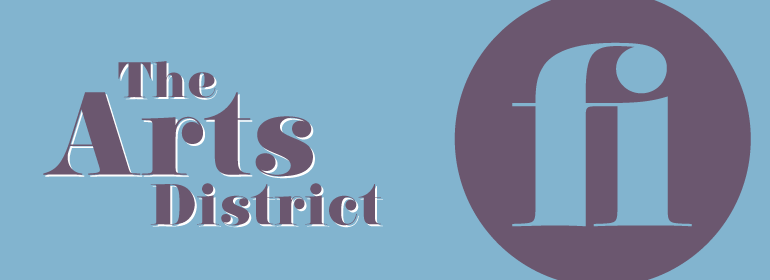
Carousel™
Carousel™,这款字体结构工整、笔画清晰,兼顾美观与易读性,适用于标题、正文、海报、包装、LOGO 等多种场景。字形优雅稳定,风格百搭耐看,适配日常排版与创意设计,让文字呈现更舒适、更具质感。Carousel™一笔一画,皆是细节,以均衡的比例、流畅的线条打造舒适视觉体验,字形端正大气,风格简约现代。无论是商业设计、品牌宣传还是日常排版,都能轻松驾驭,让文字更有格调与力量。Carousel™字体下载。